어느 편집디자이너의 형식적인 이야기.1_파일 출력 100분 전
대학을 졸업하기도 전에 입사한 디자인사무실 풍경이 아직도 생생하다. 신입사원이라 특별히 주어진 일이 없음에도 늘 허둥댔던 내게 선배들의 현란한 손놀림은 그 자체만으로도 동경의 대상이었다. 나와 달리 선배들은 항상 여유롭기만 했다. 가장 인상 깊었던 것은 며칠, 아니 몇 주에 걸쳐 완성한 방대한 데이터를 출력소로 넘기기 전, 불과 두어 시간 만에 새로운 디자인으로 탈바꿈시키던 사수의 모습이었다. 거의 100분 정도 걸렸으려나.
출력소(지금은 인쇄소로 직접 보내는 경우도 있음)로 데이터를 보내기 전 100분이라는 시간을 과연 편집 디자이너들은 어떻게 활용하고 있을까. 보통은 클라이언트 혹은 담당 편집자와 함께 오탈자를 수정하거나, 이미지 모드 및 해상도 정리, 간단한 레이아웃과 오브제의 컬러 변경, 단락 확인 등의 최종 점검 단계를 거치고 있을 터다. 누군가는 종이 샘플이나 컬러칩을 뒤적이며 마지막까지 인상을 찌푸리고 있을 수도 있겠다. 완성된 화면을 바라보며 여유롭게 커피를 마시는 낙천적인 디자이너의 모습도, 상상 해본다.
나 또한 이런 과정을 거친 후에 인쇄소와 통화하지만, 몇 년 전부터는 다른 과정으로 그 시간을 채우고 있다. 어쩌면 이 글은 우리 사무실 편집장이 앞서 연재한 오른쪽 흘리기 및 줄바꿈에 대한 실무 버전이라 할 수도 있겠다. 그런 이야기만으로는 아무것도 해결되지 않으니까. 좀 더 나은 오른쪽 흘리기를 실현하고자 노력했던 경험들, 그리고 디자이너 자신이 가장 적절하다고 판단한 단락 스타일을 기본적으로 적용한 이후의 이야기다.
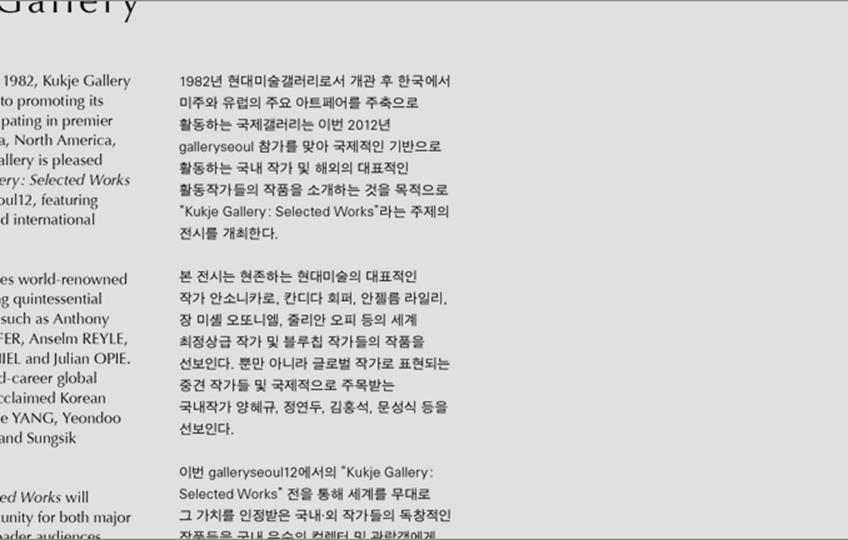
글줄의 시작 지점
글줄의 시작 지점은 언제나 무질서한 상태로 보인다. 기껏 오른쪽 흘리기 여부를 놓고 클라이언트를 설득하는 데 성공했지만, 나름의 글자 간격과 글줄 간격을 지정한 글상자에 텍스트를 흘려놓으면 글줄의 시작 지점에 군데군데 보이는 이 빠진 듯한 모습이 생기곤 한다. 게다가 시작 지점에 한글이 아닌 알파벳이라도 올 때면 왼쪽 정렬(또는 오른쪽 흘리기)이라는 말이 무색할 정도다. 나름대로 최적이라고 생각하는 글줄 간격, 단어 간격, 글자 간격을 유지했다 하더라도, 더불어 운 좋게 자연스럽게 흐르는 리듬감 있는 형태까지 갖췄다 하더라도 시작 지점이 고르지 않다면 그것은 이상적인 오른쪽 흘리기의 모습이 아닐 게다.
그 불안정한 시작 지점을 만드는 대표적인 요소 가운데 하나는 따옴표다. ‘구두점 내어쓰기’라는 기능으로 약간 보정할 수 있겠지만, 각각의 구두점 너비 및 지정 공간이 다르고 다음 글자와의 간격이 달라서 일정 간격으로 입력하기엔 또 다른 어색함을 동반하기 마련이다. 만약 커닝을 ‘시각적’으로 지정했다면 다음 글자의 초성에 따라 그 간격은 또 달라진다. 해당 단락의 시작 지점에 가장 넓게 차지하는 따옴표를 기준으로 나머지 글줄을 들여쓰기 해줘야 비로소 칼에 베일 정도의 시작 지점을 얻을 수 있다.
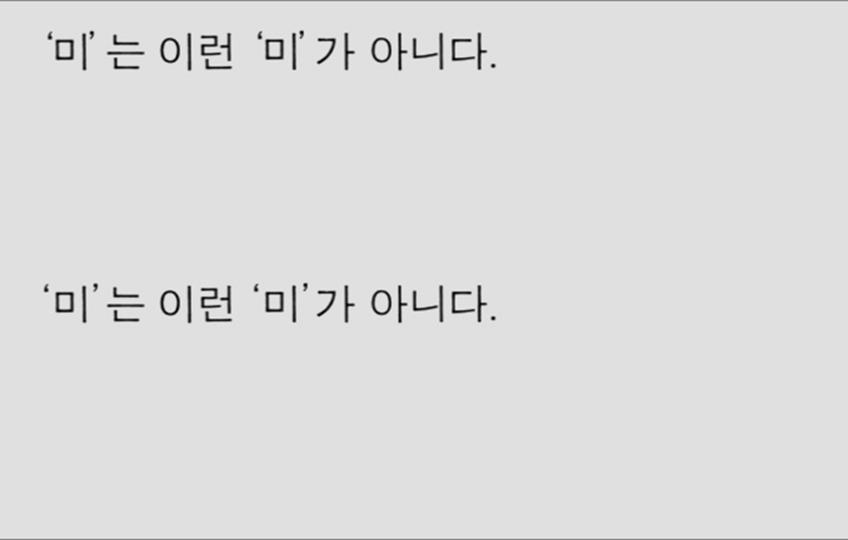
따옴표와 앞뒤 글자와의 간격
여담으로 예전에 쿽익스프레스를 사용하면서 가장 불만스러웠던 점 중 하나는 따옴표와 앞뒤 글자와의 간격이었다. 유난히 붙어 있는 그것들은 다음 글자의 초성이 ‘ㅂ, ㅁ, ㅍ’일 때 최악의 간격을 보여준다. 그럴 때마다 보이는 족족 간격을 조정하곤 했는데, 매번 볼 때마다 그 기준이 달라져서 속이 타는 느낌으로 그 시간을 보냈던 기억이 있다. 지금은 어느 정도 개선된 프로그램 성능 때문에 그 수고를 덜지만 초성마다 달라지는 간격을 소화하기엔 여전히 만족스럽지 않다. 게다가 같은 문단에서 글꼴이 변경된다 싶으면 경우의 수는 기하급수적으로 늘어나기 때문에 스타일을 지정한다는 것은 확인 과정만으로 엄청난 시간을 동반할 수밖에 없다. 개인적인 감각으로 판단하는 게 오히려 정신 건강에 좋다.
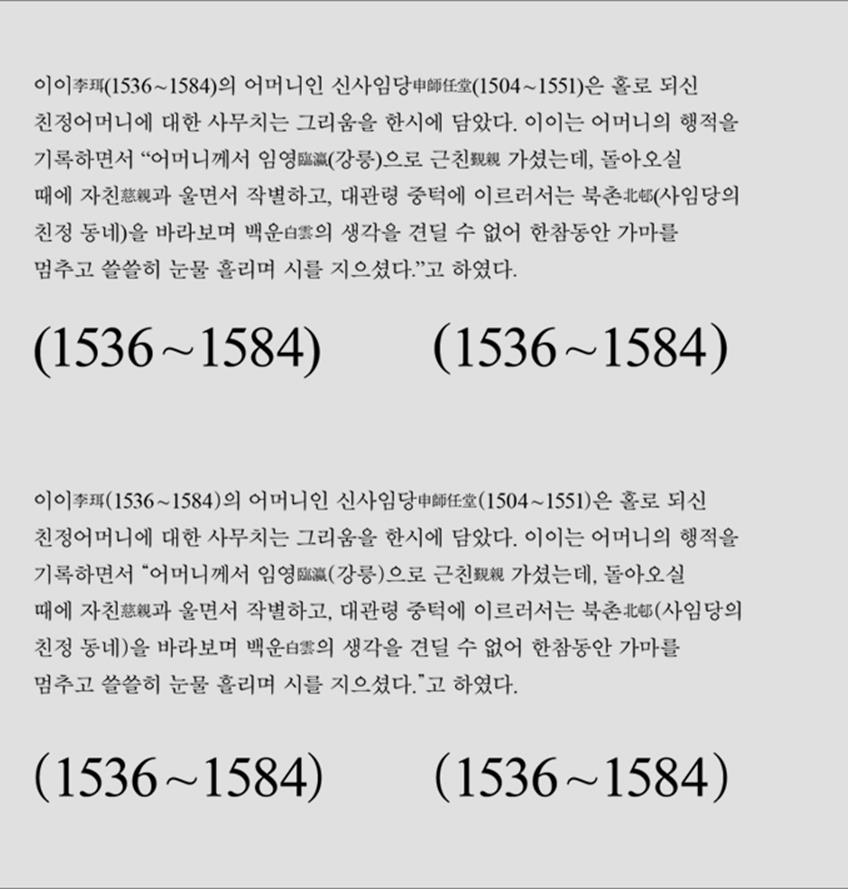
괄호 조정
다음은 괄호다. 괄호의 종류도 여러 가지라서 일일이 그것들에 대한 조정을 나열하지 않고 기본적인 ‘( )’에 대한 조정만 살펴보려고 한다. 먼저 한글 글꼴과 알파벳 글꼴의 그것이 서로 다르다는 점을 이야기하고 싶다. 내 주위의 몇몇 디자이너들은 한글과 알파벳이 섞인 글(때론 섞이지 않은 한글 단락도 있음)을 다룰 때 문장부호를 알파벳 글꼴로 지정하는 경우가 종종 있다. 그 이유는 아마도 합성글꼴 만들기의 용이함, 포함된 알파벳이나 숫자와의 어울림, 아니면 구두점 내의 공간을 효율적으로 이용하기 위한 것으로 생각된다.
내 경우엔 글의 주를 이루는 언어에 따라 그것을 선택한다. 구두점의 크기 및 기준선이 두 언어 안에서 다르기 때문이다. 물론 크기와 기준선을 조정한 값을 스타일로 지정할 수 있겠지만 구두점까지 주가 아닌 언어로 바꾸는 게 왠지 사치스럽게 여겨진다. 어쨌든 선택한 글꼴의 괄호는 두 언어의 기준선이 다르기 때문에 앞뒤 문자의 종류에 따라 조정할 수밖에 없다. 또한 주된 언어가 한글일 때 괄호 안에 알파벳이나 숫자만으로 이루어진 단어가 올 경우 시작 괄호와 다음 글자의 간격, 맺음 괄호와 그 앞의 글자와의 간격이 다를 수밖에 없다.
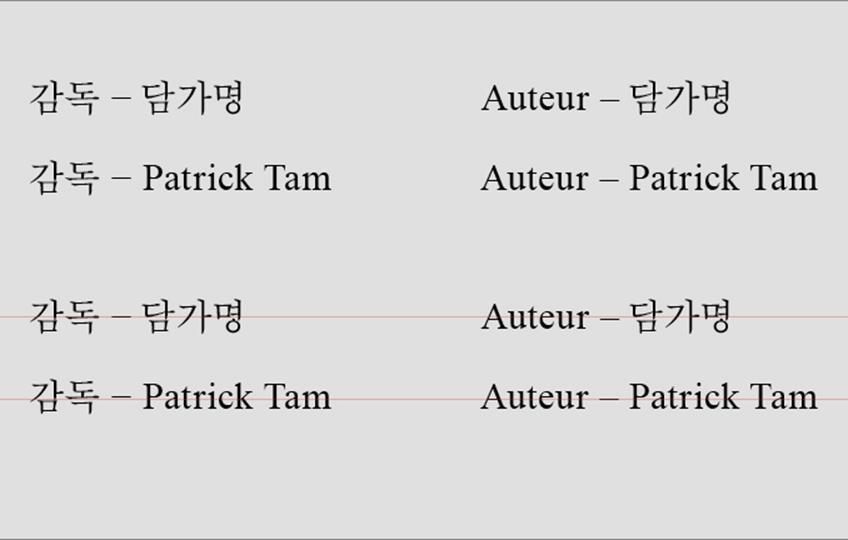
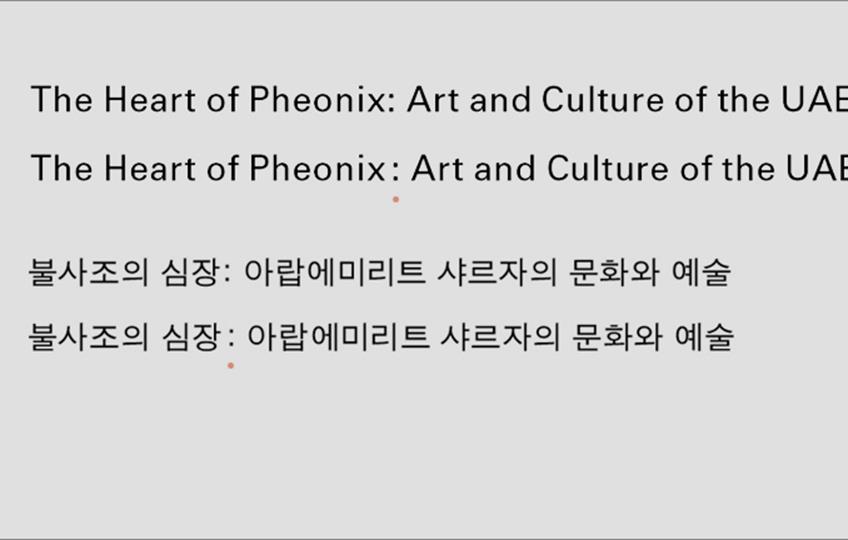
대쉬, 환점, 쌍점, 반쌍점 등의 부호들
괄호와 함께 ‘대쉬(-), 환점(.), 쌍점(:), 반쌍점(;) 등 세로 중심이 민감한 부호들 또한 기준선 정렬이 중요하다. 특히 쌍점과 반쌍점은 앞 글자와의 간격도 신경 써야 한다. 앞뒤 간격의 조정이 필요한 것 가운데 또 한 가지는 온점(.)을 제외한 마침표들이다. 물음표와 느낌표가 대표적인데, 문장의 형식을 나타내는 이들은 보통 마침표(온점)에 비해 앞 글자와의 간격이 좁아 보인다. 이들의 높이가 글자의 높이만큼을 유지하기 때문일 텐데, 알파벳은 물론 한글도 조정이 필요한 경우가 있다.
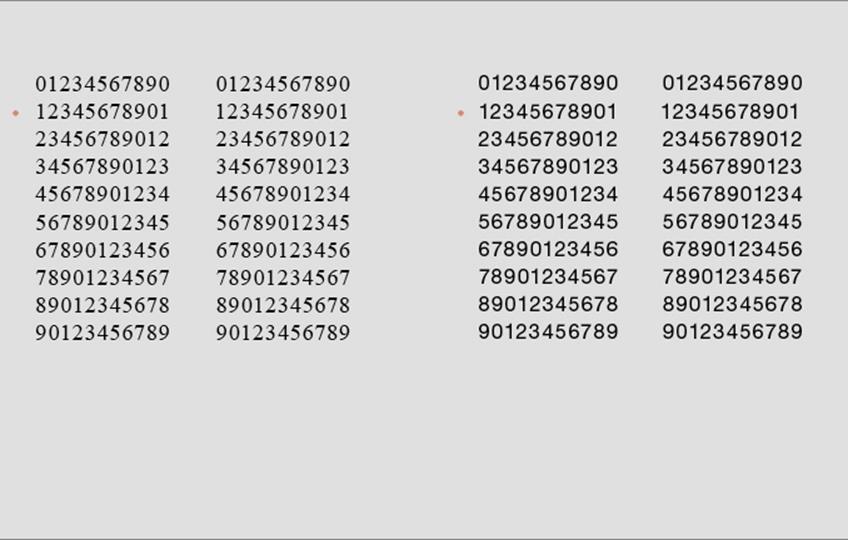
숫자
숫자 또한 시작 지점의 균일함을 방해하는 요소인데, 그 중에서도 ‘1’은 나머지 숫자와 다른 시작 지점을 갖고 있어서 때에 따라 들여쓰기와 내어쓰기의 조정이 필요하다. 다행히 글꼴 대부분의 ‘1’은 한글의 시작 지점과 동일하게 두어도 어색하지 않아 다른 아홉 개의 숫자만 조정한다면 무리가 없다. 또한 알파벳의 시작 지점에 그 아홉 개의 숫자의 것을 포함시키기도 하는데, 작품의 캡션이나 판권 부분에 주로 적용한다.
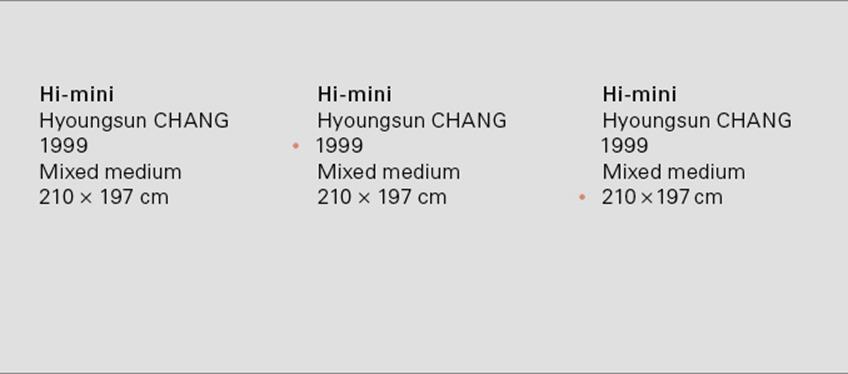
캡션에 들어가는 기호들
작품 캡션에는 이 외에도 여러 기호가 들어가곤 하는데, 각각의 크기를 연결시켜주는 ‘×’와 단위를 나타내는 ‘cm, mm’ 등이 그것이다. 예를 들어 ‘210 × 197 cm’의 크기를 가정한다면 ‘2’의 시작지점, ‘0’과 ‘×’와 ‘1’의 간격, ‘7’과 ‘cm’의 간격을 조정한다. 단락의 주요 시작 지점을 한글로 둔다면 ‘2’는 약간 들여써야 할 것이고 벌어진 ‘0’과 ‘×’와 ‘1’의 간격은 약간 줄여야 한다. 또한 ‘×’와 ‘1’의 간격은 ‘1’ 앞의 내부 공간 때문에 ‘0’과 ‘×’의 간격보다 더 줄여야 균일한 간격으로 보인다. 마지막으로 ‘7’과 ‘cm’의 간격 조정인데, ‘cm’의 해당하는 수치가 앞의 모든 내용이므로 ‘0’과 ‘×’와 ‘1’의 간격보다 더 넓어야 한다.
일일이 이 정도 조정을 진행하고 나면 보통 얼굴이 붉게 변한다. 이럴 때면 간단한 작업으로 쉬어 가는데, 무심코 지나쳤던 띄어쓰기 조정이다. ‘찾기/바꾸기’를 활용해 단어 사이에 있는 두 칸을 고르는 과정이다. 가끔 단락 사이나 표 짜기에 설정해놓은 태그를 망각하고 ‘모두 변경’을 누르면 일이 걷잡을 수 없이 커지기 때문에 이 역시 하나하나 확인해가며 한 칸을 삭제하는 편이 안전하다. 두 칸, 때에 따라서는 그 이상의 띄어쓰기가 발견될 때마다 개운한 느낌과 함께 원래의 얼굴빛을 찾을 수 있다.
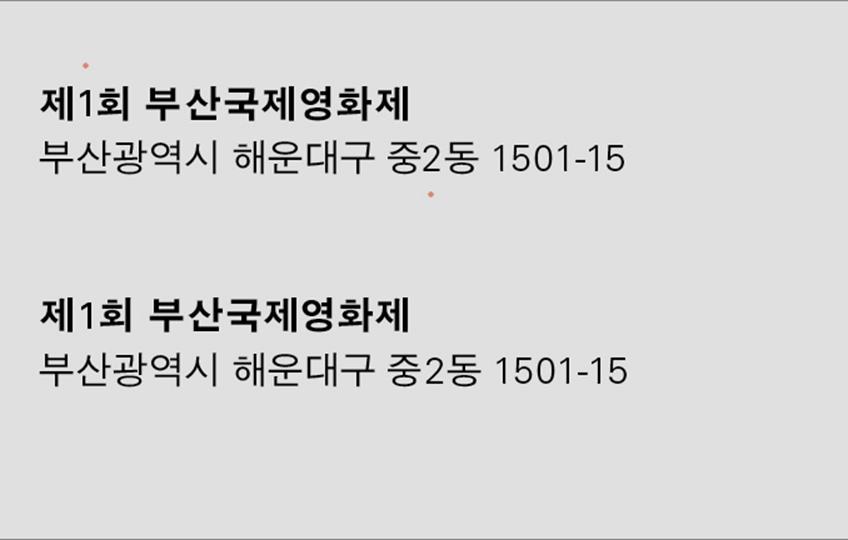
한글 뒤 간격 조정
다음은 한글 뒤에 띄어쓰기 없이 숫자나 알파벳이 바로 오는 경우의 조정이다. ‘제1회’, ‘중2동’ 정도로 예를 들어보자. 해당 문자에 한글과 알파벳 글꼴을 각각 적용했을 때 두 가지의 조정은 반대로 적용할 수밖에 없다. 글꼴에 따라 차이가 있지만 앞의 경우엔 ‘제’와 ‘1’의 간격이 ‘1’과 ‘회’의 간격보다 넓고, 뒤의 경우엔 ‘중’과 ‘2’ 사이의 간격이 ‘2’와 ‘동’의 그것보다 좁기 때문이다. 앞의 경우엔 숫자와 뒷글자 사이를 넓히고, 뒤의 경우엔 숫자와 앞글자 사이를 넓혀야 한다. 만약 숫자와 알파벳 이외의 부호에도 알파벳 글꼴을 적용했거나 숫자 앞의 문자가 한글꼴 기호가 오더라도 마찬가지일 것이다.
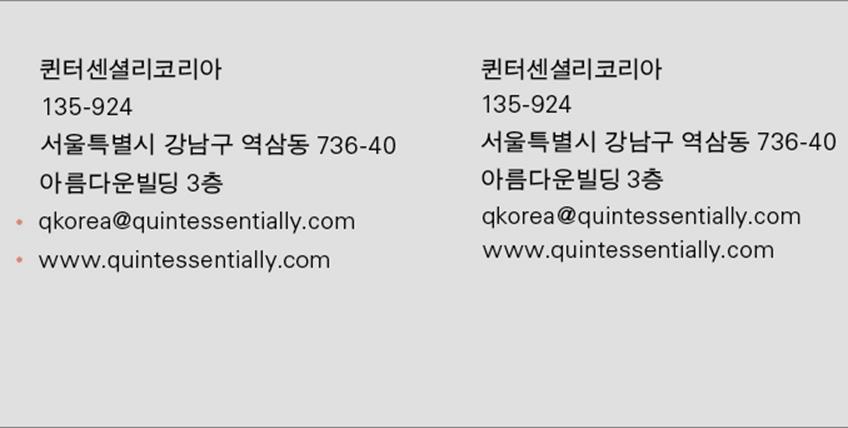
다른 언어끼리의 글줄 간격 조정
같은 글줄이 아닌 다른 글줄에서 다른 언어끼리 줄이 구분된다면, 다른 조정이 필요하다. 보통 주소 및 연락처, 메일과 홈페이지의 주소가 이에 해당하는데, 한글주소 다음 줄에 소문자만으로 구성된 메일과 홈페이지 주소가 이어질 때 확연히 드러난다. 대문자 높이에 해당하는 문자는 ‘@’나 ‘/’ 정도여서 실제 글줄의 높이는 소문자의 x-height로 인지하기 때문이다. 이런 경우에는 옆 단락의 유무나 내용의 길이에 따라 필요한 만큼의 글줄 기준선을 조정한다. 물론 앞서 나열했던 시작 지점의 정렬과 동시에 ‘@’, ‘/’, ‘:’ 앞뒤의 간격 조정도 함께 이루어져야 한다.
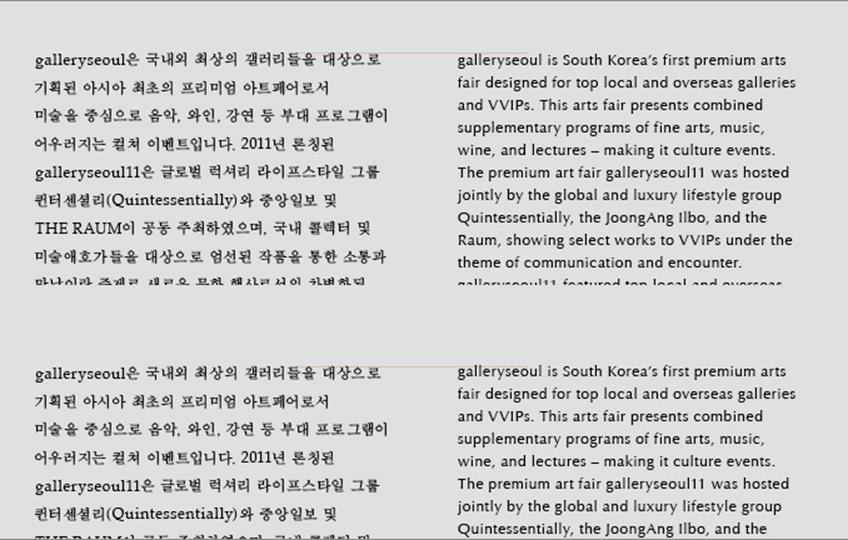
단락끼리의 간격 조정
그렇다면 더 나아가 글줄이 아닌 단락끼리의 조정은 어떠할까? 여기에서 이야기하고자 하는 것은 최적의 단락 사이의 간격이 아닌 동일한 시작지점(Y축)을 갖는 서로 다른 언어가 각기 다른 단락을 구성하고 있을 때의 조정이다. 워크룸은 국영문이 혼용된 도록 작업을 많이 하기 때문에 민감한 부분이다. 같은 크기의 글꼴을 같은 시작 지점(Y축)에서 배열한다 하더라도 보통 알파벳 단락이 한글 단락보다 낮아 보인다. 이것은 일반적인 문단이었을 때, 즉 대문자가 문장의 시작 부분에만 적용되었을 경우를 말하는데, 이 또한 알파벳 단락의 시작 지점을 x-height의 높이부터 인지하기 때문이다. 한글의 시작 지점은 글자마다 달라서 나름대로의 평균값으로 이것을 해결해야 한다.
글자 크기가 다를 때의 단락 높이 조정
마지막으로 페이지 번호가 남았다. 물론 ‘페이지 번호 매기기’를 통해 일정한 장소에 정확하게 수고 없이 마무리할 수 있겠지만, 각 페이지의 레이아웃에 따라 비대칭으로 구성하기 위해 직접 입력하곤 한다. 또한 앞서 언급했듯 ‘1’의 시작 지점이 나머지 아홉 개 숫자의 시작 지점과 현저하게 다르기 때문에 상단의 이미지 혹은 글단락의 시작 지점과 동일하게 정렬하곤 하기 때문이다. 또한 내 경우엔 수동으로 쪽번호를 입력하는 건 한 권의 책을 만드는 사람으로서 지켜야 할 일종의 도리처럼 간주하는 이유이기도 하다.
솔직히 지금까지 열거한 정렬의 대부분은 학부에서 타이포그래피 과정을 이수한 디자이너라면 다들 알고 있는 내용이다. 어쩌면 이런 사사로움보다는 작업 컨셉을 한 번이라도 더 점검하며 큰 그림을 본질에 가깝게 수정하고 완성하는 게 훨씬 중요할 수도 있다. 그럼에도 별것 아닌 내용을 대단한 것인 양 늘어놓은 이유는 편집 디자이너에게 주어진 마지막 시간은 작업의 완성도를 높일 수 있는 중요한 시간이라는 점을 강조하기 위해서다. 출력소에 데이터 보내는 시간을 클라이언트에게 조금만 속이면 되는 일이다.